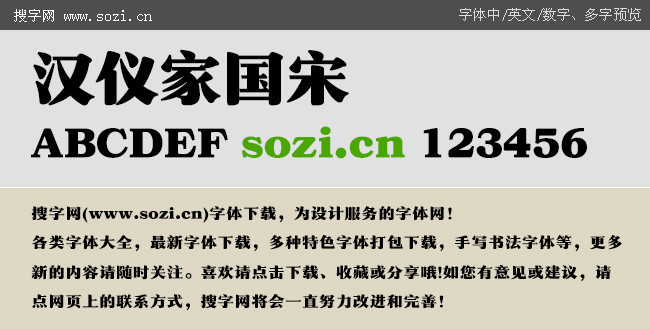
漢儀家國宋
搜字網(wǎng)給大家提供一款漢儀家國宋簡體中文字體下載,漢儀家國宋是一款具有新中國時(shí)代精神的標(biāo)語字體,他傳承了當(dāng)年美術(shù)字的革命氣息,圓潤飽滿的字型與傳統(tǒng)嚴(yán)謹(jǐn)?shù)乃误w結(jié)構(gòu)相結(jié)合,為這款字營造出一種醒目、沉穩(wěn)、奮進(jìn)、質(zhì)樸的氣質(zhì)。適用于畫冊設(shè)計(jì)、海報(bào)設(shè)計(jì)、包裝設(shè)計(jì)等場合使用。(本字體為個(gè)人非商用版,如需要商用請聯(lián)系漢儀公司購買版權(quán))